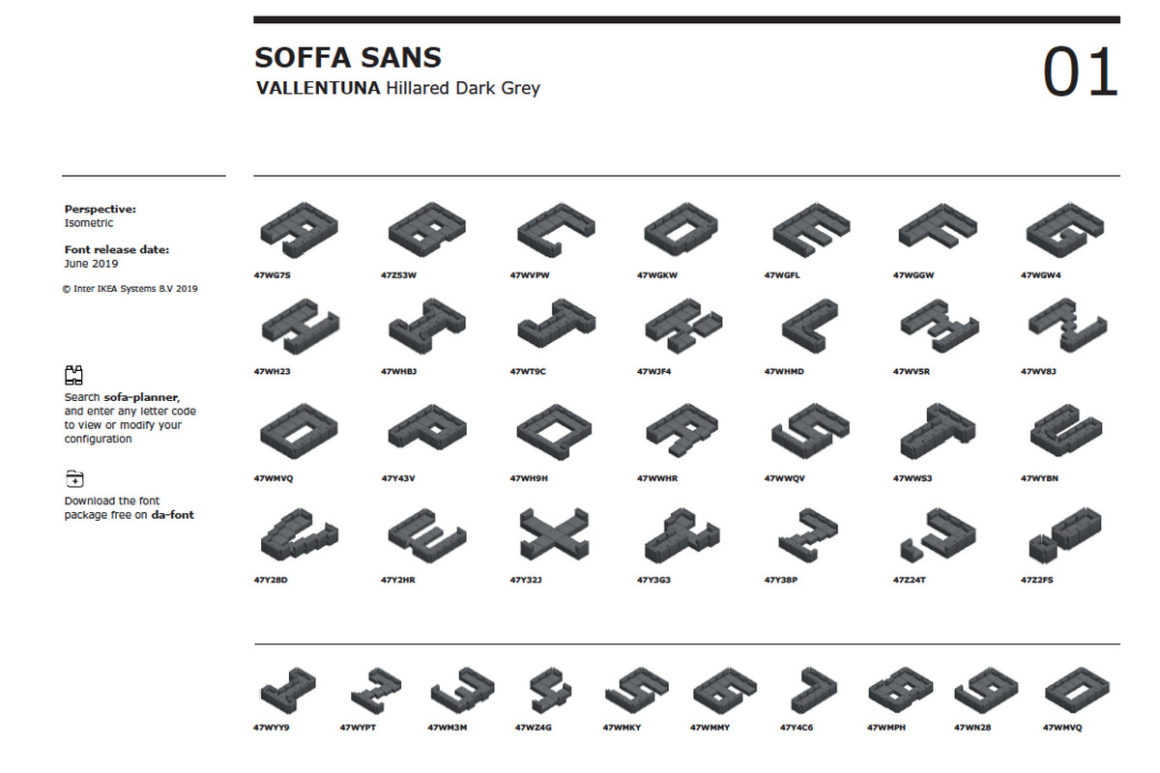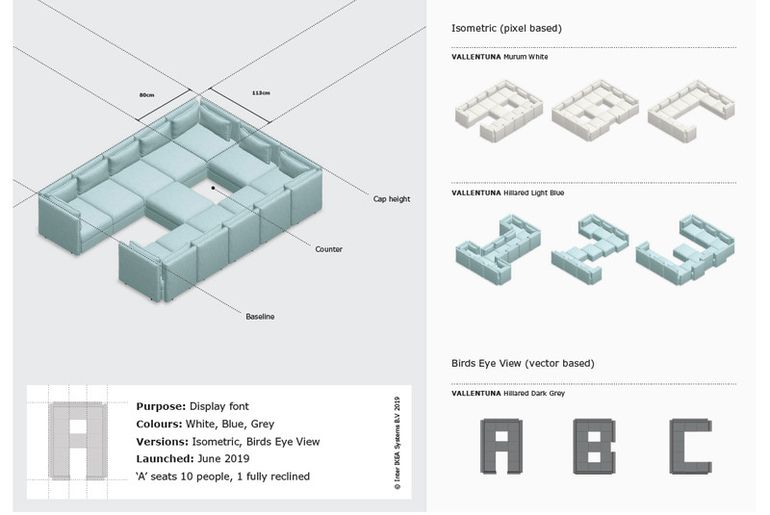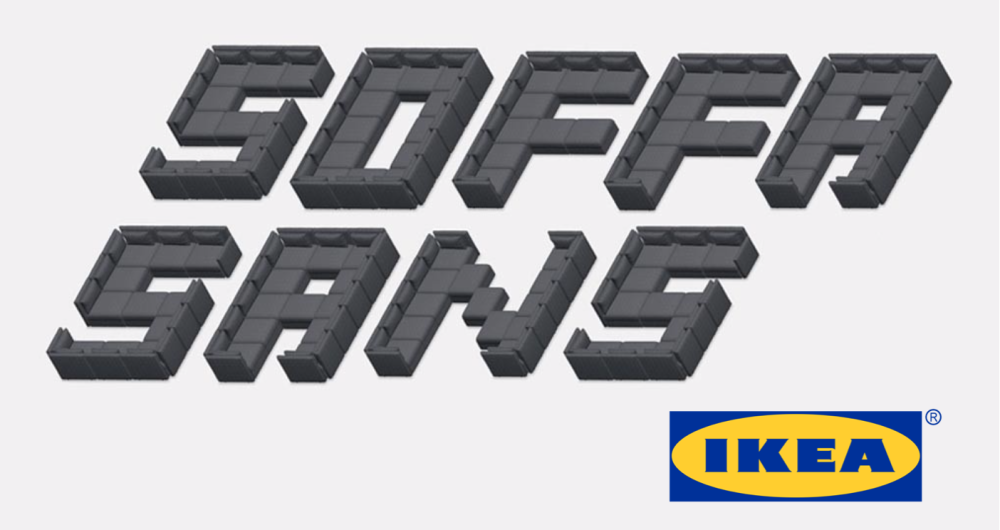
IKEA crée une typographie confortable en forme de canapé
La typographie est un art qui laisse énormément de liberté à ses créateurs car il est possible de créer une typographie avec presque tout et n’importe quoi.
Si on utilise souvent Helvetica ou Arial, sachez que des artistes s’amusent eux à aller bien plus loin dans le délire des typographies. On retrouve par exemple des typographies créées à base de poils de jambes, pour ne citer que cet exemple loufoque.
De son côté, IKEA et l’agence Proximity London ont décidé de créer la leur… en forme de canapé. Pour cela, ils se sont inspirés de l’outil « Vallentuna sofa planner » qui permet à n’importe qui de créer son canapé sur mesure, permettant même de créer des sofa aux dimensions surnaturelles.
À partir de cet outil, IKEA a alors créé Soffa Sans, la première typographie en forme de canapé. On retrouve donc toutes les lettres de l’alphabet et les chiffres avec des couleurs différentes. Mais attention, si vous souhaitez commander toutes les « lettres canapé » dans la vraie vie, sachez qu’il vous faudra débourser la modique somme de 135 000$.
Un moyen efficace pour IKEA de confirmer son positionnement de marque qui stimule la créativité de ses consommateurs. Avec cette démarche, elle montre également qu’elle n’hésite pas à innover en donnant des outils originaux aux internautes, lui permettant presque de s’immiscer dans la pop culture.